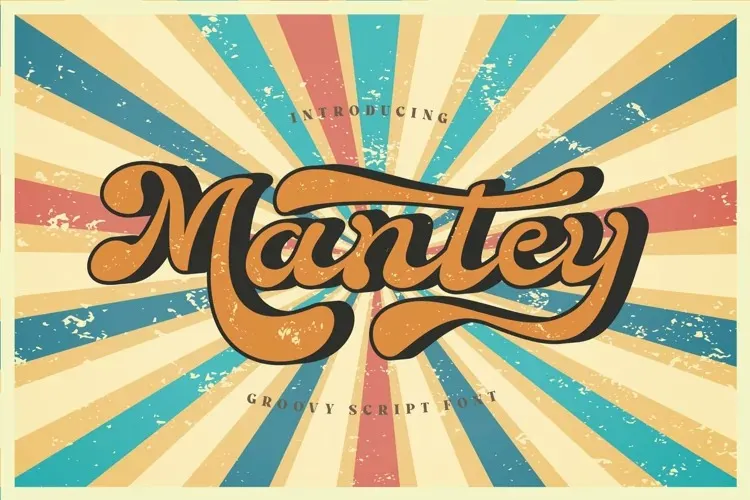
Mantaey Font – Fonte Grátis
Mantaey Font
Esta fonte script é uma pausa divertida dos tempos modernos, inspirada nos arquétipos vintage dos anos 70. Ela é brilhante e elegante ao mesmo tempo, com um tom desconcertantemente alegre que faz dela algo inconfundível. Inspirada na arte de uma era onde o design tinha alma, essa fonte traz consigo uma vivacidade vibrante que não se limita à superficialidade; seu charme é imediatamente reconhecível e memorável. Suavizada por seu caráter brilhante e elegante, Mantaey proporciona um contrastes perfeitos para textos de diferentes funções. É ideal para aplicativos em que o design precisa ter um toque único e desafiadormente agradável aos olhos – seja ele um site de notícias vintage ou uma revista gráfica que transmite um tom casual mas elegante. Sem sombra de dúvidas, Mantaey oferece um conjunto perfeito para quem busca tanto versatilidade quanto originalidade. É a escolha ideal para aqueles desejando destacar suas criações com um toque vintage e inovador simultaneamente. Seja o próximo projeto que você está trabalhando em desenvolvimento, Mantaey é uma fonte script que certamente fará você se sentir mais confiante ao criar algo novo e agradável de forma simples e envolvente.